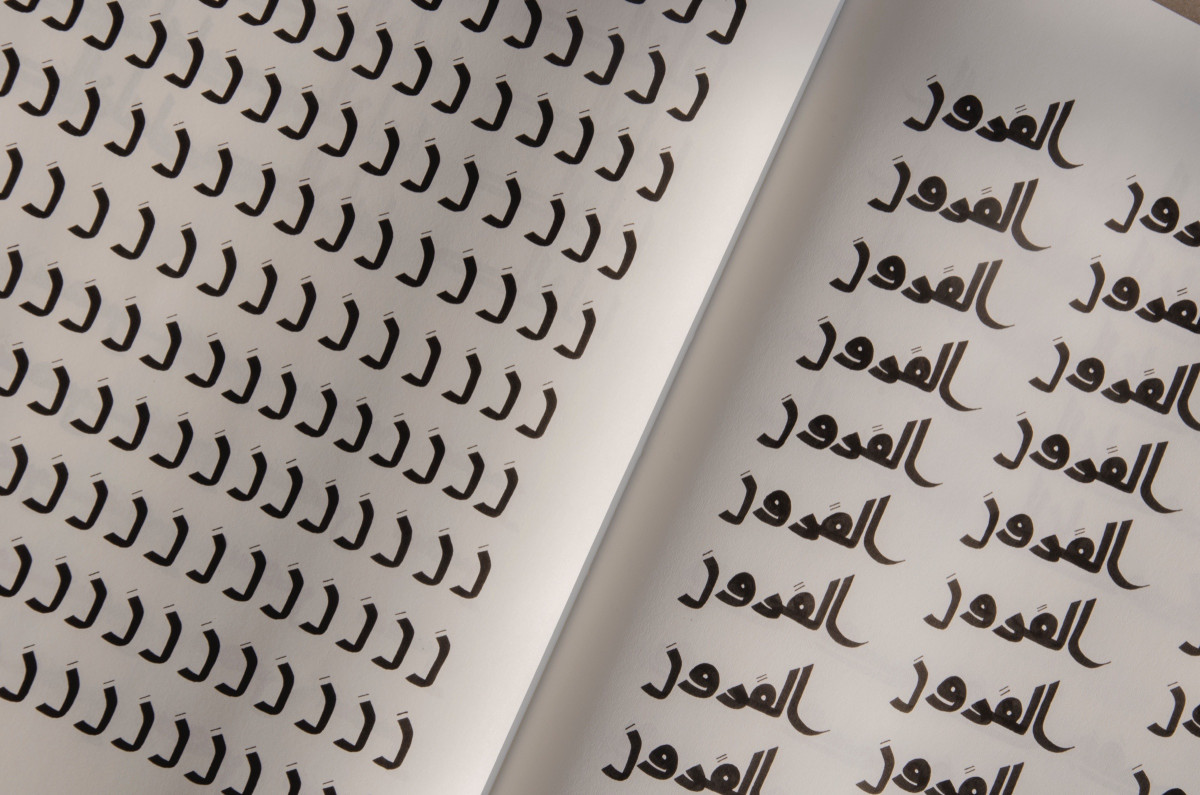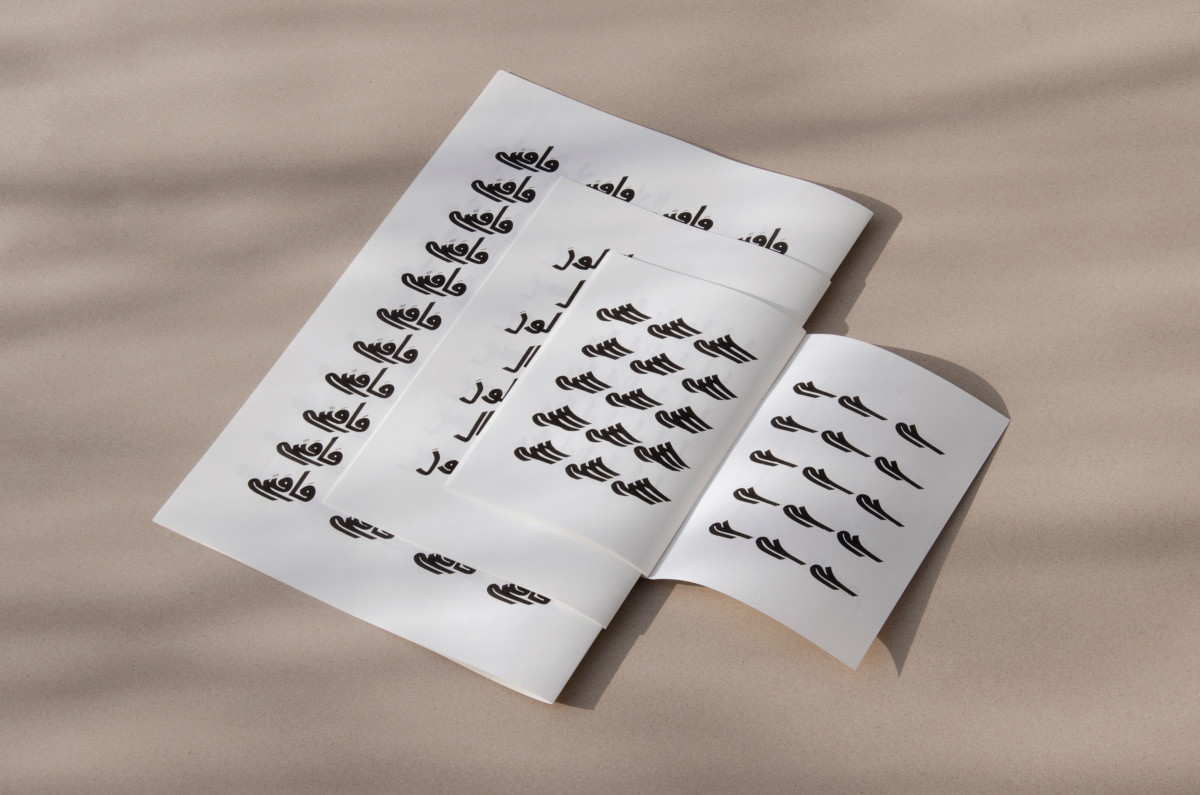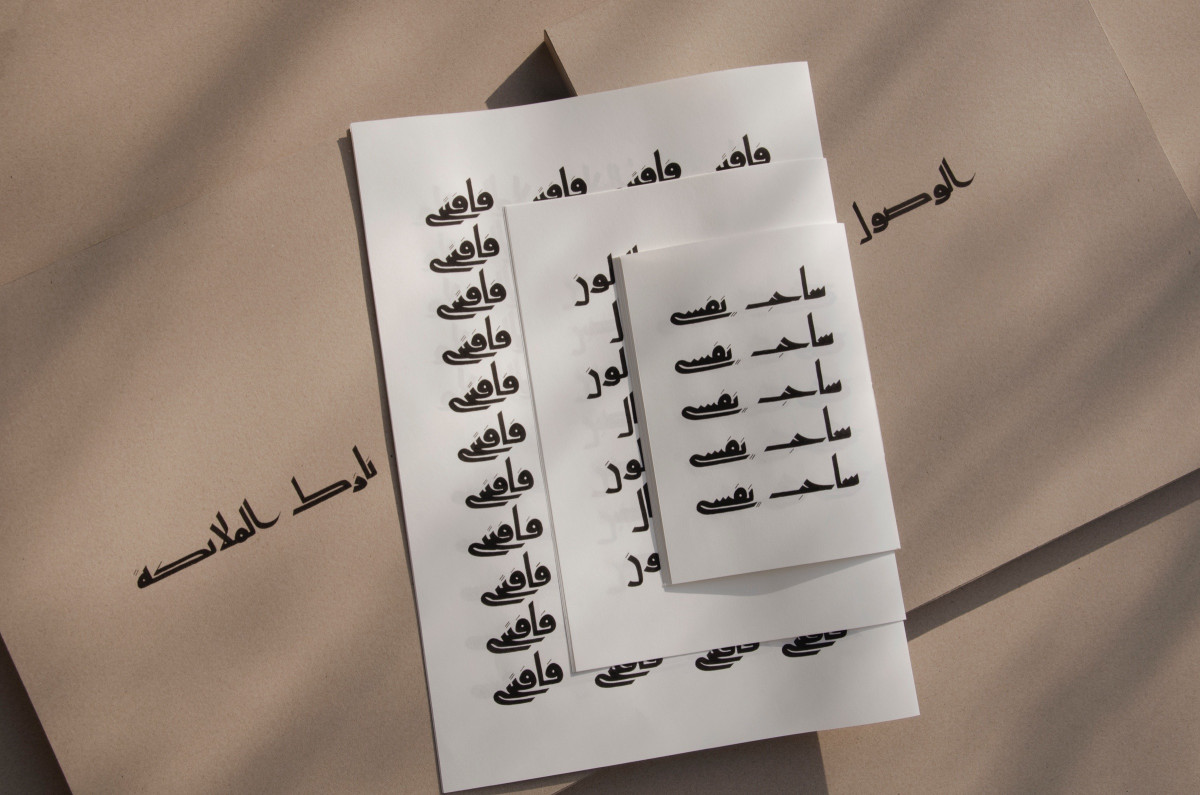
„Ich werde meine Seele lieben, im Beben ihrer Schatten leben Jahrhunderte, erfüllt von den Farben der Fantasie.“
Mit diesen Worten beginnt das Gedicht – Die Ankunft – der irakischen Dichterin Nazik Al-Malaika. Die künstlerische Arbeit ist eine Annäherung des Gedichts und bewegt sich zwischen Lyrik, Schrift und Selbstliebe. In dieser experimentellen Auseinandersetzung entfalten sich einzelne Worte durch kalligraphische Übungen – ein meditativer Prozess des Schreibens, Wiederholens und Verinnerlichens.
“I will love my soul, in the trembling of its shadows live centuries, filled with the colours of fantasy.”
The poem – The Arrival – by the Iraqi poet Nazik Al-Malaika begins with these words. The artistic work is an exploration of the poem and moves between poetry, writing and self-love. In this experimental exploration, individual words unfold through calligraphic exercises – a meditative process of writing, repetition and internalisation.